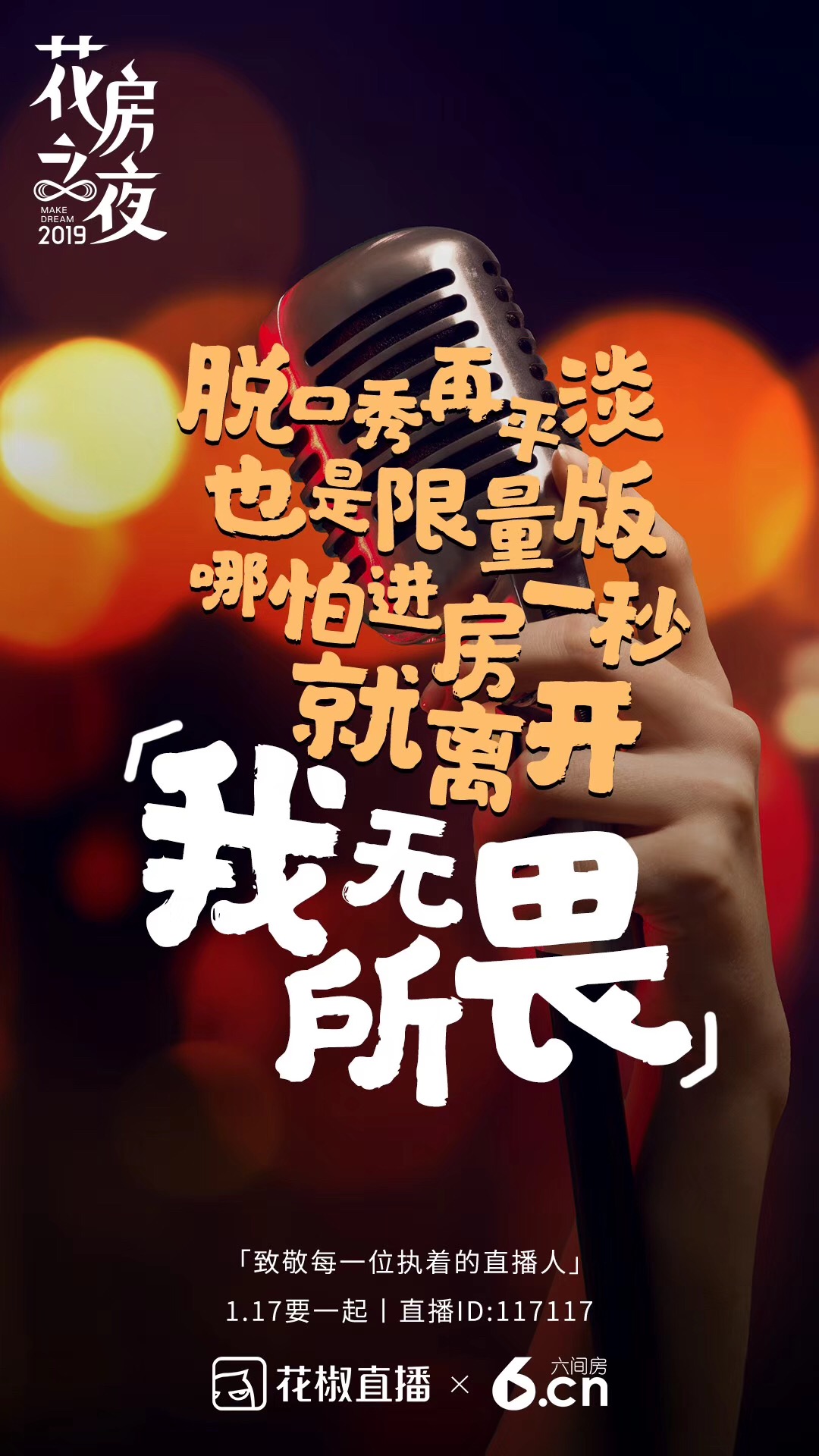
方正呐喊体
于彦舒
创意书写
2013
方正呐喊体由漫画家于彦舒创作,试图表达一种呐喊、自嘲、发泄的情感,来排解年轻人在网络生活中的负面情绪。这款字体的笔画刚硬狂野,与浮动的方框形成鲜明的对比,如一个人强烈试图挣脱某种困境。方正呐喊体的风格激情沸腾,适用于励志类的广告和产品包装设计,以及社交网络的个性化用字。